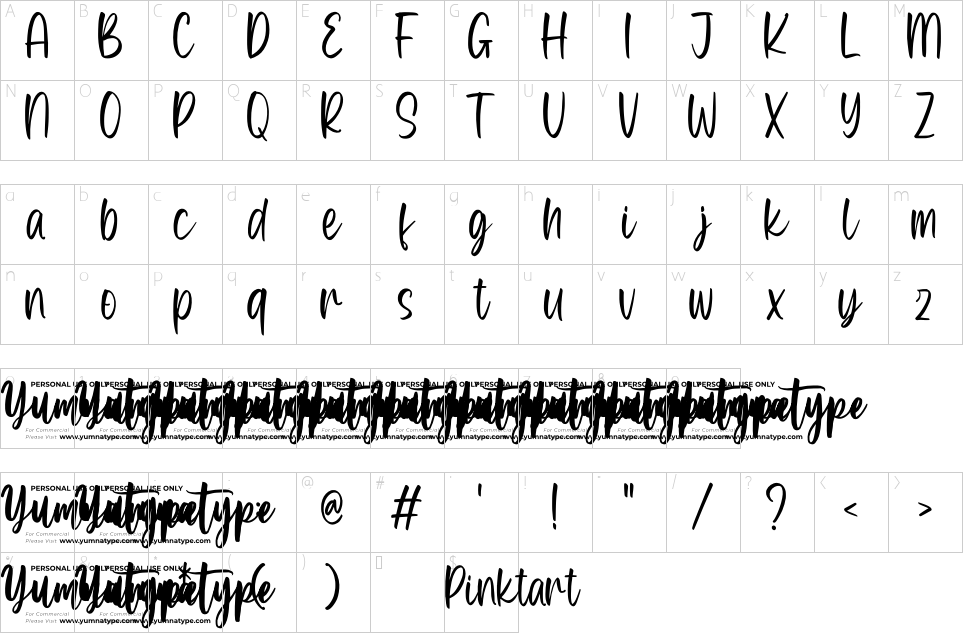
Pinktart Font – Fonte Grátis
Pinktart Font
Descubra a brilhante Pinktart Font para suas criações digitais com esta descrição envolvente. Desenvolvida por Yumna Type, Pinktart é uma fonte elegante que traz à vida um toque de charme às suas produções. Ideal para trabalhos gráficos que exigem uma sensação alegre e viva, essa fonte garante um visual irresistivelmente bonito e único. Com seu design cuidadosamente criado, a Pinktart não apenas enriquece o texto mas também adiciona um toque especial ao design de ícones ou qualquer outro elemento gráfico. Com uma facilidade de uso sem igual em tanto Windows quanto Mac, esta fonte é perfeita para designers que valorizam simultaneamente beleza e funcionalidade. Descubra hoje a versatilidade da Pinktart e transforme seus projetos digitais no ponto de encontro entre o belo e a tecnologia.
Mapa de caracteres da fonte Pinktart Font